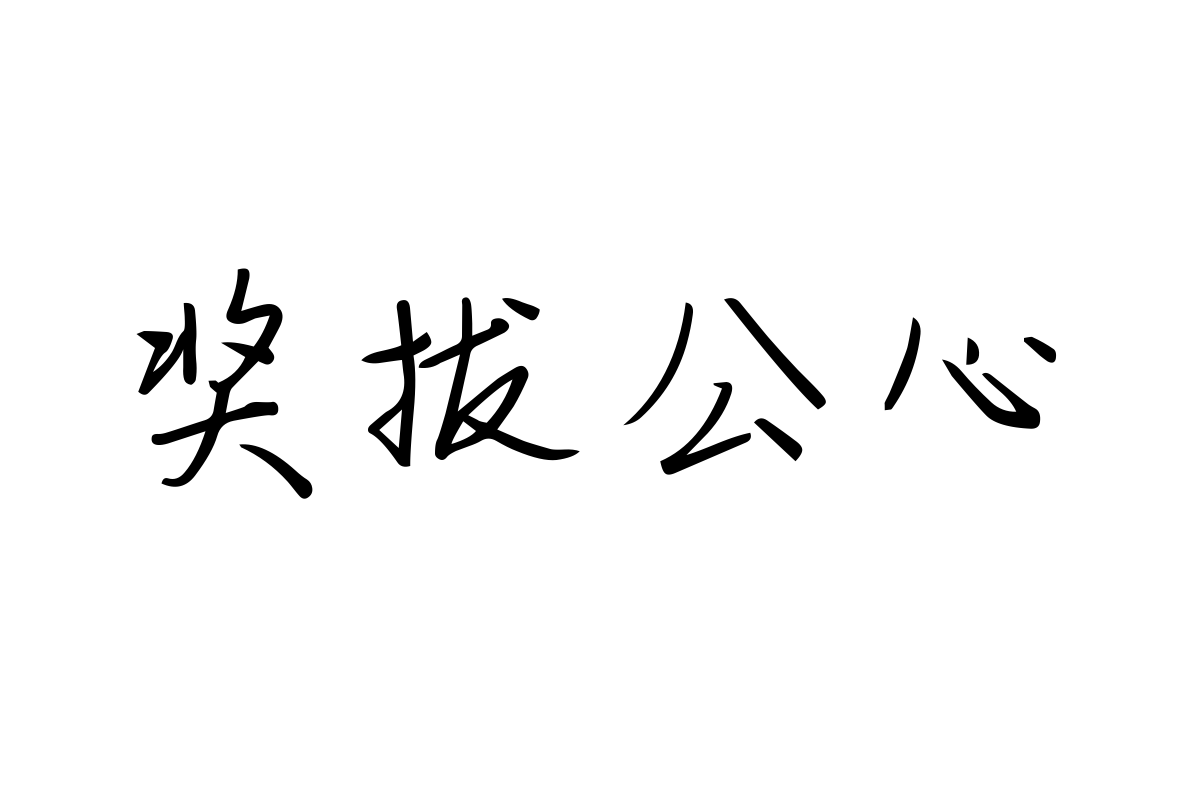
仓耳独白体是一种新型的中文字体,它由仓耳设计工作室开发。该字体具有独特的设计风格,包括简洁的线条和清晰的字形结构。它的笔画粗细适中,易于阅读和书写,同时保持了一定的艺术感。
仓耳独白体的主要特点是其独特的“仓耳”风格,这种风格将传统的汉字书法元素与现代设计理念相结合,创造出既具有传统韵味又不失现代感的字体。此外,该字体还注重细节处理,如笔触的粗细变化、笔画的转折处的处理等,使得字体更加生动有趣。
总的来说,仓耳独白体是一款适合用于各种场合的文字设计工具,无论是在网页设计、海报制作还是书籍装帧等领域,都能展现出其独特的魅力。